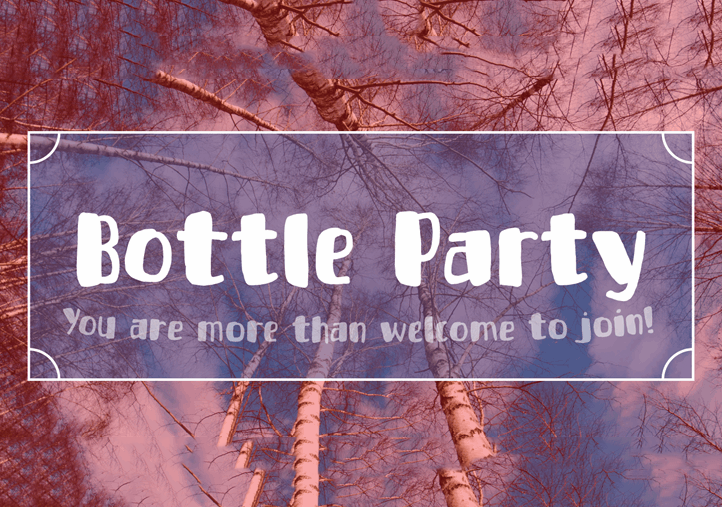
A fonte ‘Bottle Party Font’ é uma seleção única de brush fonts desenvolvida pelo designer Pizzadude.dk. Inspirada na festa divertida de champanhe, esta font oferece uma maneira inovadora para criar textos únicos e coloridos sem precisar digitar cada palavra por si mesmo. Uma das características mais interessantes desta font é a capacidade do texto não repetir letras idênticas em sequência. Ao escrever com essa fonte, os caracteres alternativos são automaticamente introduzidos conforme você digita, permitindo que as letras diferentes apareçam sempre que necessário. Além disso, ‘Bottle Party Font’ está disponível em quatro versões de cada letra minúscula, garantindo uma variedade constante e fresca para qualquer texto. O designer fez um trabalho meticuloso na construção da fonte, adicionando um toque brush que torna-a ainda mais atraente. Embora seja feita para textos grandes e detalhados, ‘Bottle Party Font’ é tão legível em pequenas escala quanto em grande, o que significa que você pode usá-la em qualquer aplicação de design gráfico sem perder o poder visual. Além disso, a fonte incorpora uma ampla gama de caracteres internacionais para facilitar a criação de textos multiculturais. Este design de brush oferece aos criadores um meio único e criativo para expressarem suas ideias através do texto, garantindo que cada projeto seja inovador e autêntico.